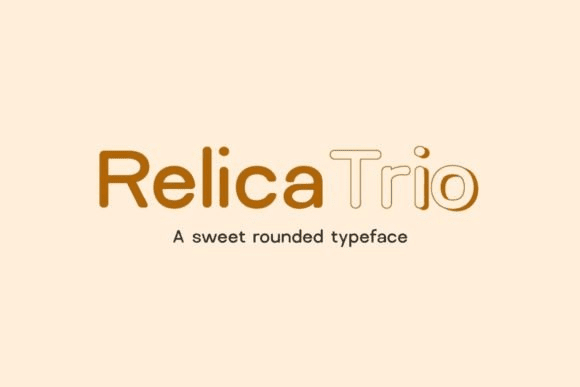
Название: Relica Trio Font (2021)
Relica - это сладкий округлый шрифт, вдохновленный брендингом продуктов питания и пекарен. Шрифт отлично подходит для логотипов, брендинга, заголовков, рекламных и демонстрационных материалов. Этот шрифт представлен в 3 различных стилях и лучше всего подходит для создания современных логотипов, рекламного контента и маркетинговой графики, которые действительно могут привлечь внимание ваших посетителей.
Название: Relica Trio Font (2021)
Relica - это сладкий округлый шрифт, вдохновленный брендингом продуктов питания и пекарен. Шрифт отлично подходит для логотипов, брендинга, заголовков, рекламных и демонстрационных материалов. Этот шрифт представлен в 3 различных стилях и лучше всего подходит для создания современных логотипов, рекламного контента и маркетинговой графики, которые действительно могут привлечь внимание ваших посетителей.